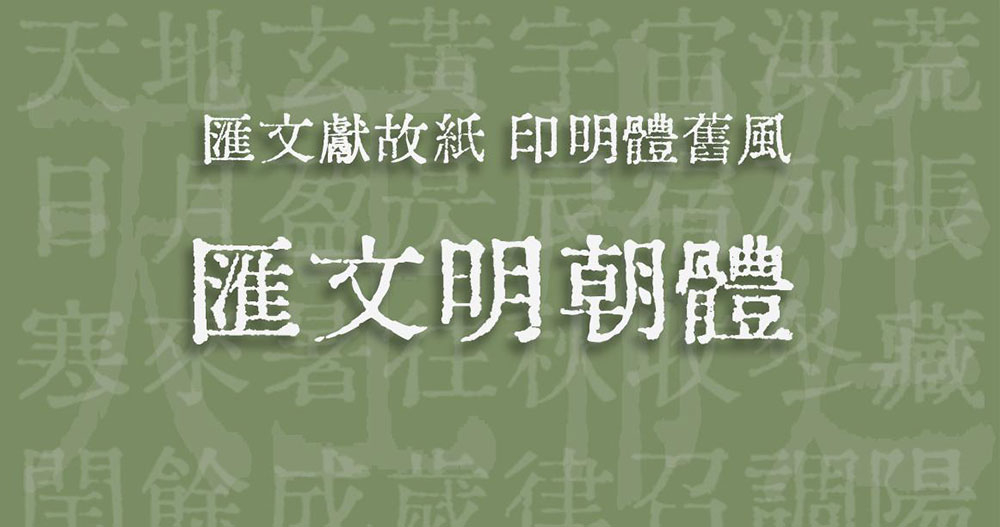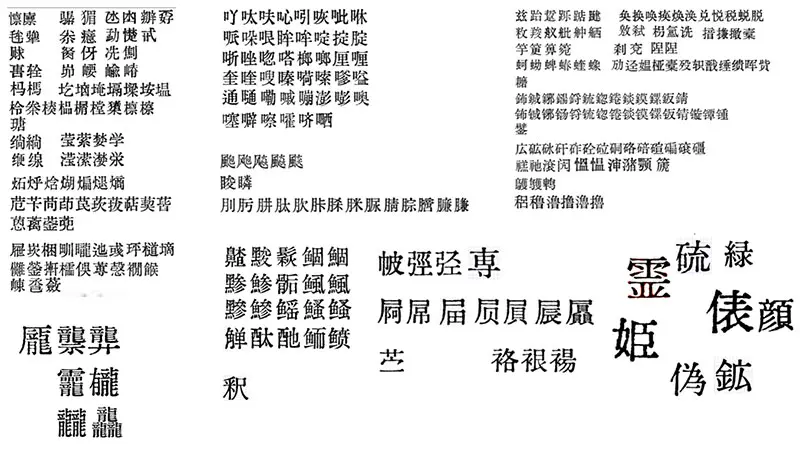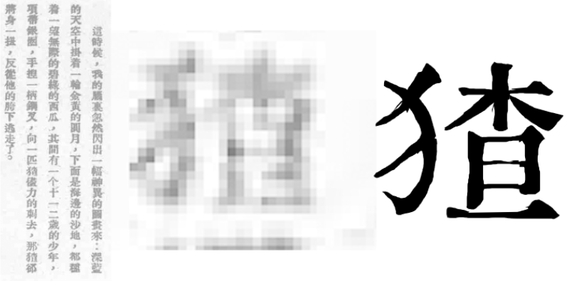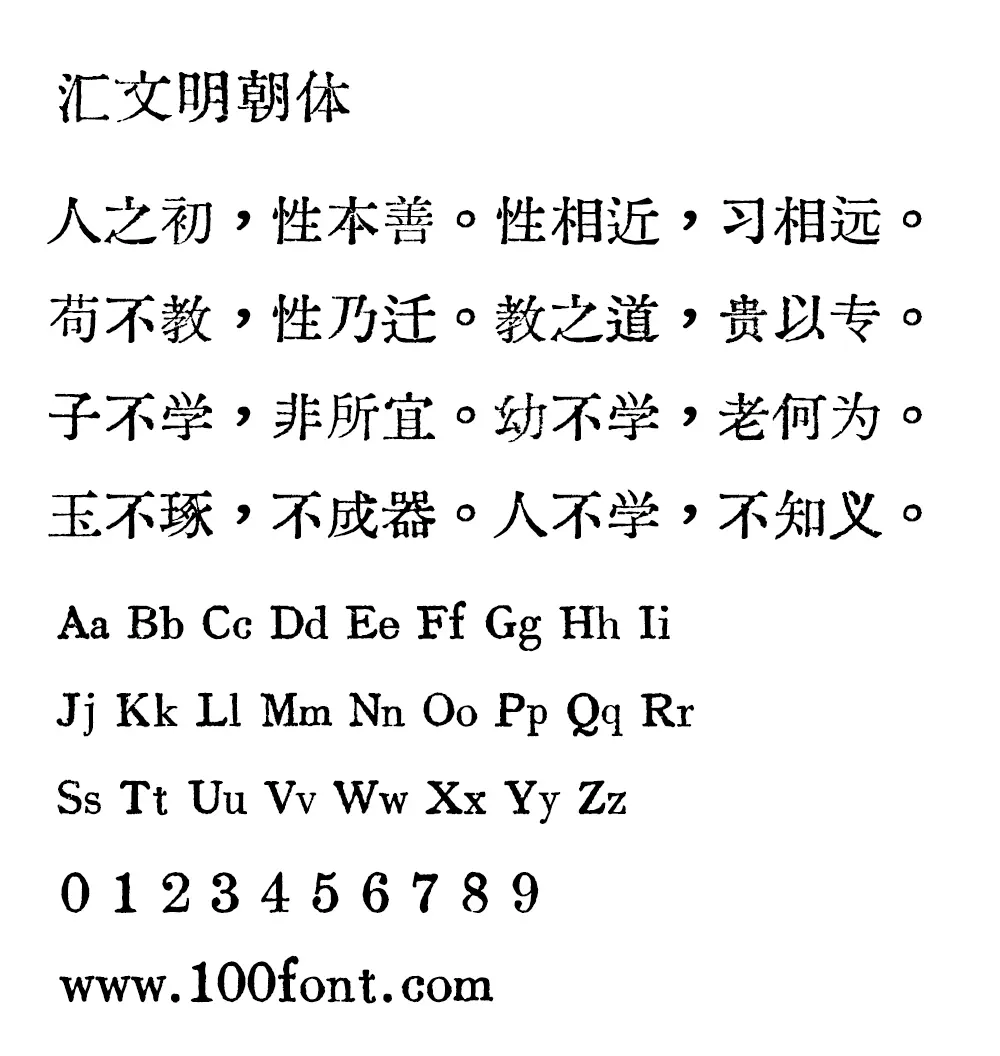
本字體制作始於2019年1月份,因一切開始於是我掃描《文匯報》上面的《漢字簡化方案草案》,後來又收集、掃描了各種歷史文獻資料,彙總挑選而形成了這樣一款字體,故名「匯文明朝體」。
本字體的字形來源主體為五六十年代官方各種漢字改革文件,簡體字部分基本復原漢字簡化後、字形改造前的書籍印刷體樣貌。繁體字、傳承字部分基本還原民國至共和國初期字形樣貌,是比較原滋原味的舊鉛字印刷風格。
收錄範圍及規則
全覆蓋大陸「GB2312」標準,全覆蓋臺灣「常用國字標準字體表」,全覆蓋日本常用、人名用、表外漢字表中的新字體,基本滿足日常使用,收錄規則大致如下:
●舊字形有單獨編碼,但是簡體漢字標準和繁體漢字標準日常都使用新字形的,都從舊(但採用不同來源讓字形有所區別)
●簡體漢字標準和繁體漢字標準使用不同編碼的,保留新字形,各從其形
●中日共有簡化字編碼相同者從中(所以日文顯示有時候很彆扭)
●中國特有簡化字從舊(按最早公佈之字形)
●日本特有新字形從舊從異
●個別罕見異體字按照個人喜好從異
●不追求部件寫法統一
字形來源
以下羅列書名按收錄先後順序排列,後收的書中如果有效果更好的字會替換掉前面的字:
簡化漢字以及所對應的繁體字,來源於《簡化漢字方案》《簡體字總表》;
傳承字,來源於《通用漢字表草案》《新華字典》;
異體字,來源於《簡化漢字方案》《第一批異體字整理表》;
日本新字形及日語常用字,來源於《新字體漢和新辭典》1995、《日本常用漢字表》上海科學技術出版社;
部分生僻字,提取自匯文築地五號明朝體(516字):
其他生僻字,來源於《語文新字典》1977星洲世界書局、《國音常用字彙》1938
基礎拉丁字母及阿拉伯數字,來源於《通用漢字表草案》、《標準電碼本》1964
俄文字母,來源於某本俄語字典前的字母表,實在找不到了……
希臘字母,來源於《日本常用漢字表》上海科學技術出版社(沒錯,希臘字母來源於一本日語書…)
注音符號,來源於《潮汕新字典》廣泰書局
其他拉丁字母、符號、平片假名及個別漢字,來源於Oradano明朝
拼字自繪(274字)
「猹」復刻自《新青年》第九卷第一號魯迅《故鄉》
本字體平片假名及一些符號來源於Oradano明朝,其實要說起來,本字體的史祖就是Oradano明朝。
因為最開始做的時候,我對於字體的字距、大小甚麼的,完全不會調,也不知道要怎麼設置各種數據,所以就直接取了「Oradano明朝」這個字體作為殼子,把裡面的東西一一替換成我的字形,慢慢地替換到最後,才形成了匯文明朝體。就是說,其實這是一艘忒修斯之船。